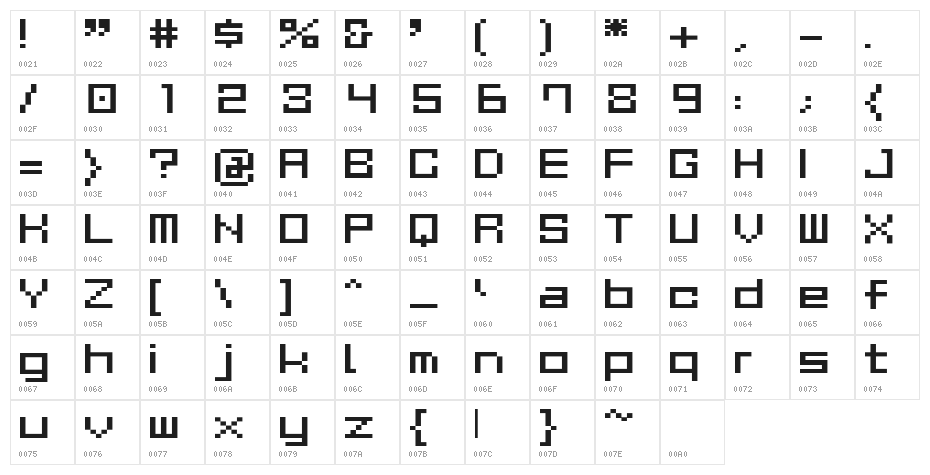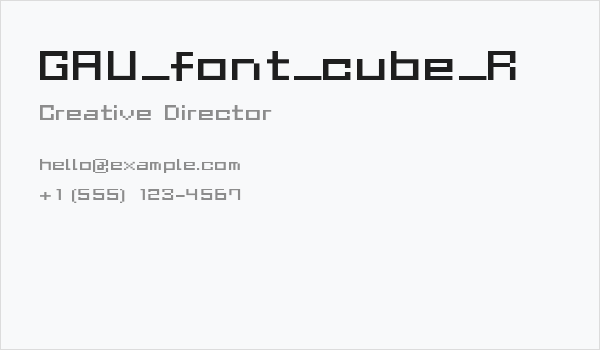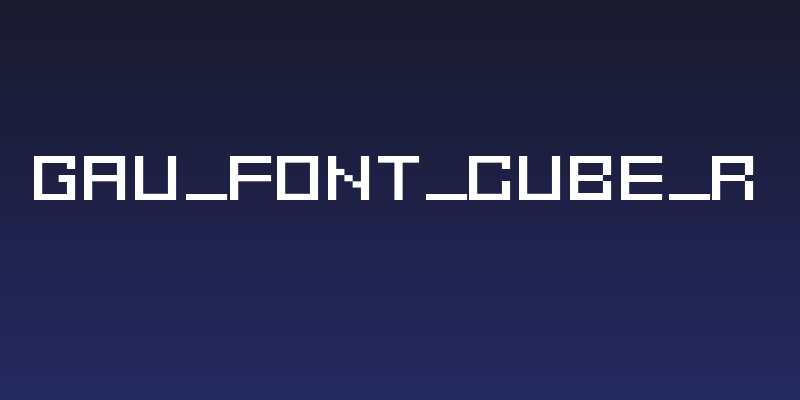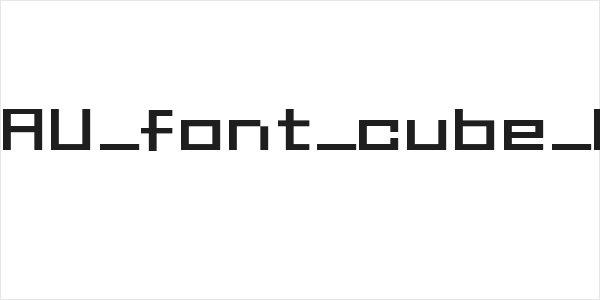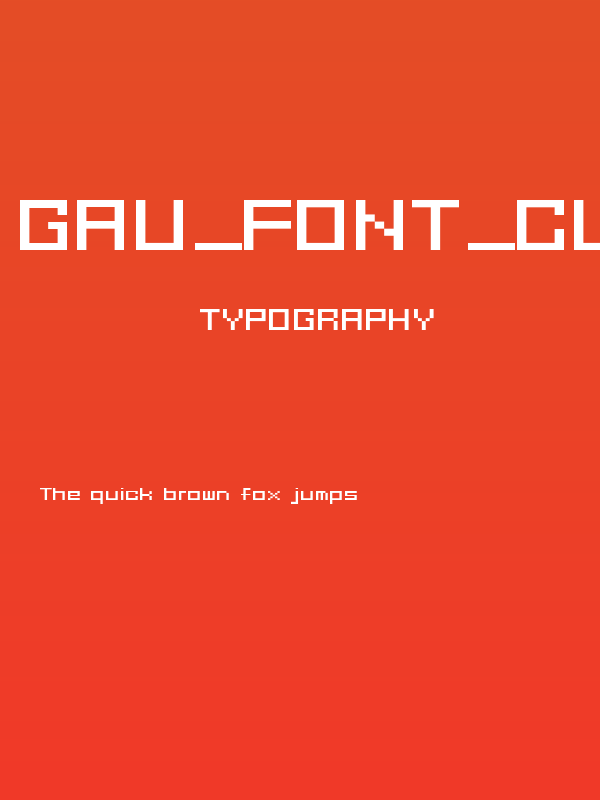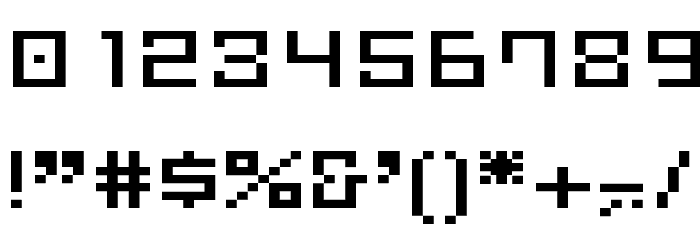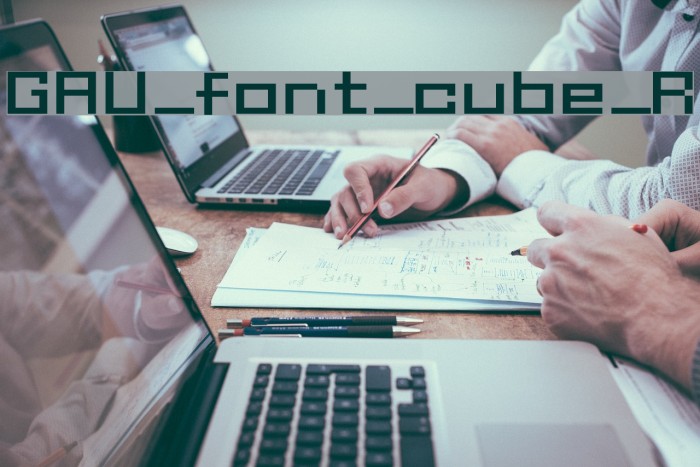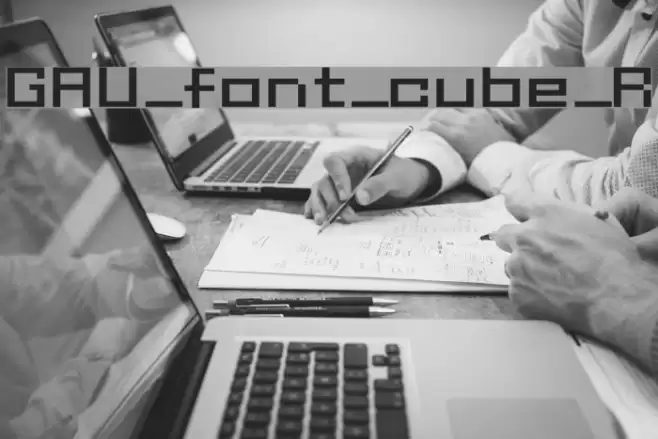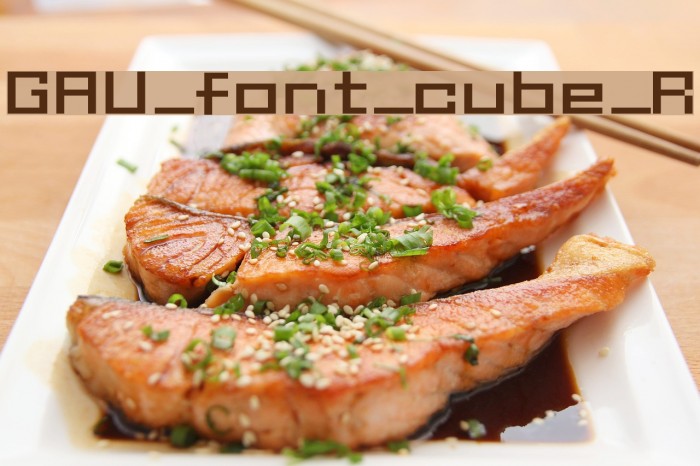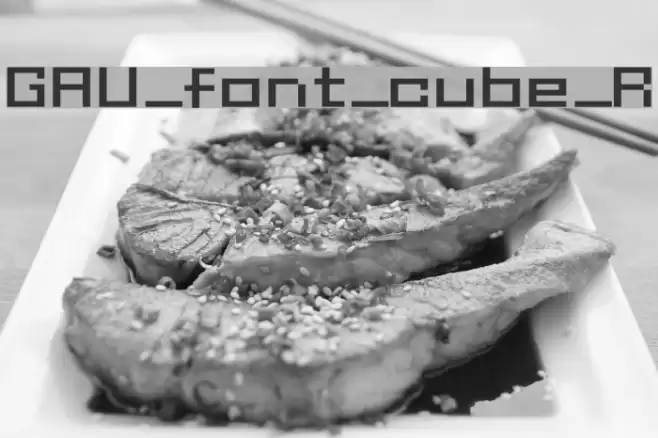
GAU_font_cube_R Font
✎ Pixel
| Estilo general | Vintage |
| Caso de uso | Logos, Headlines, Digital displays |
| Proyectos propuestos | Ideal for video game design, digital art projects, retro-themed graphics, and any creative work that seeks to evoke a sense of nostalgia for early computing. |